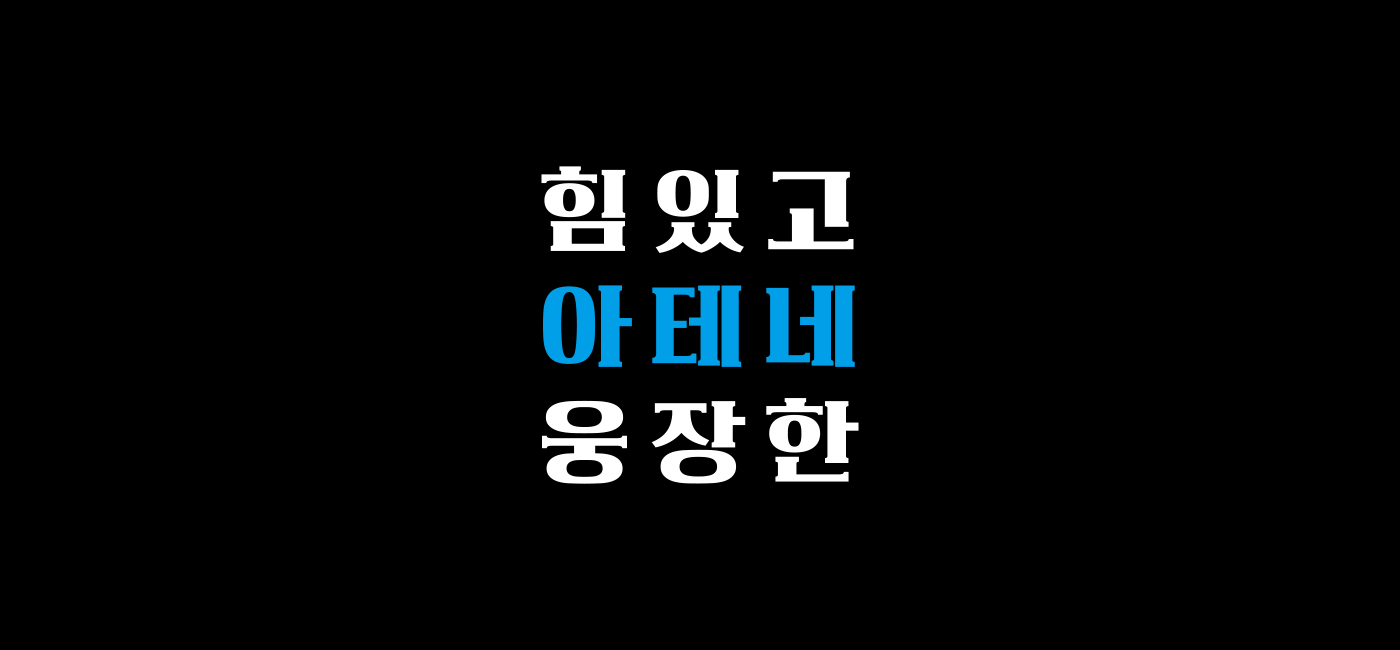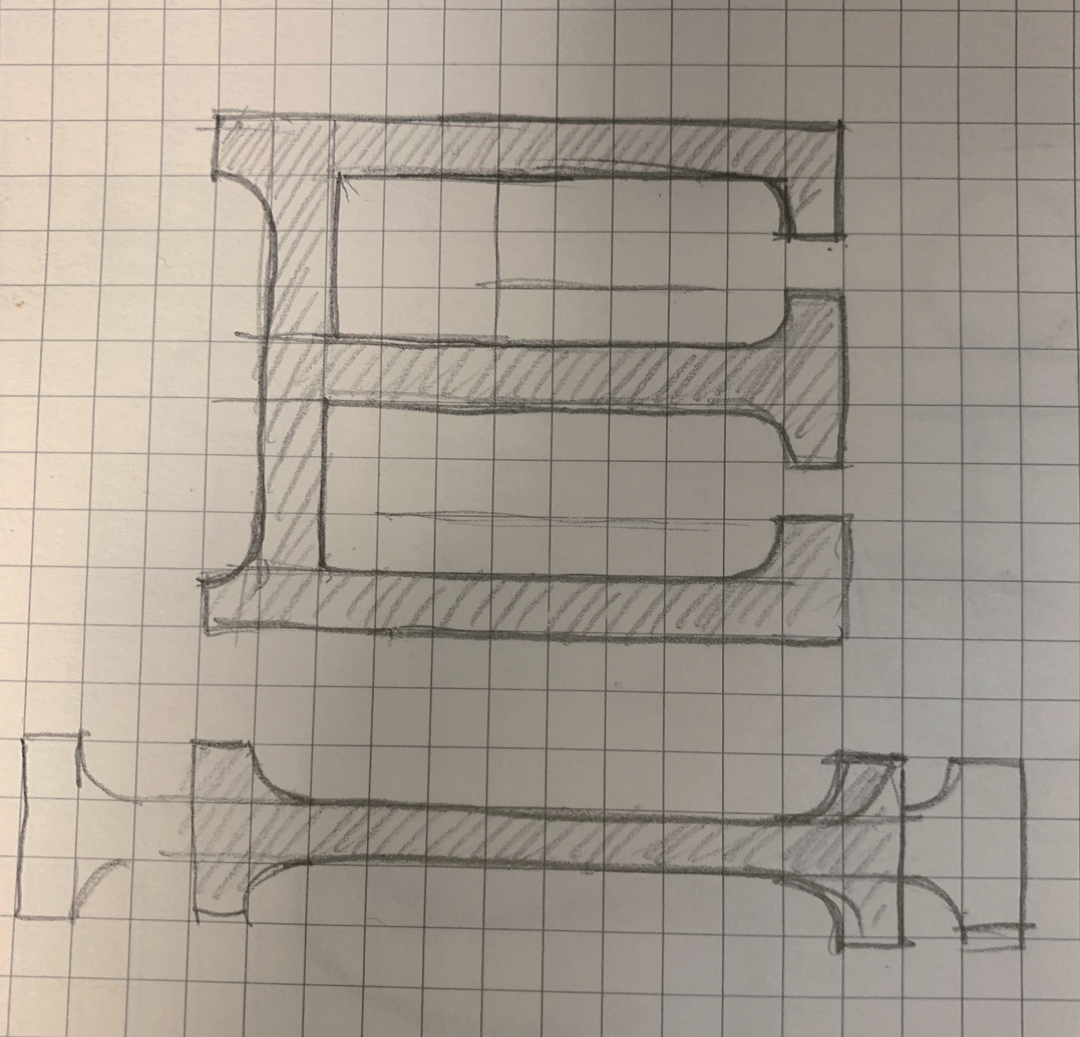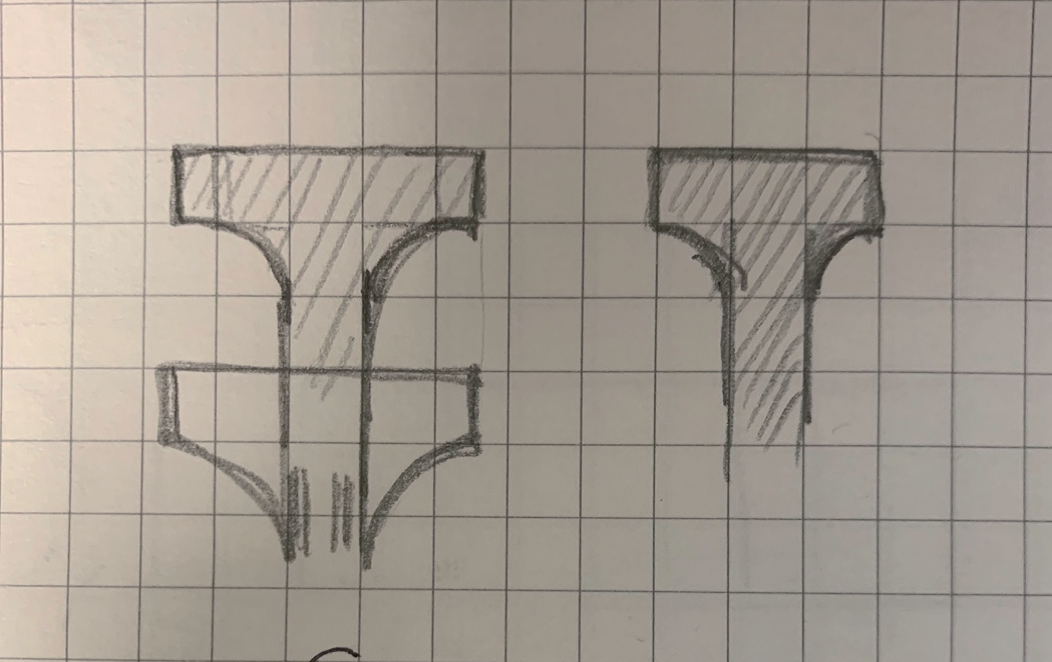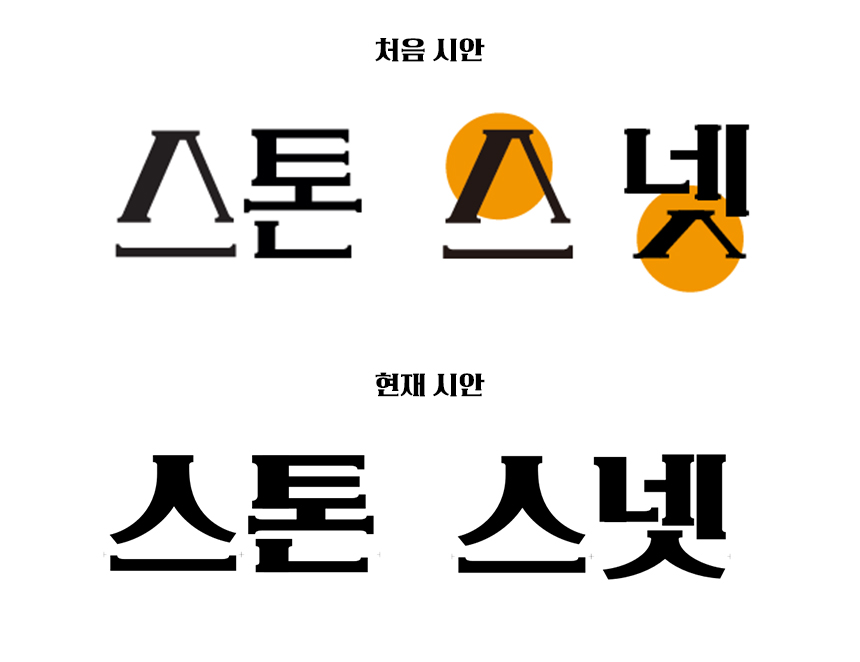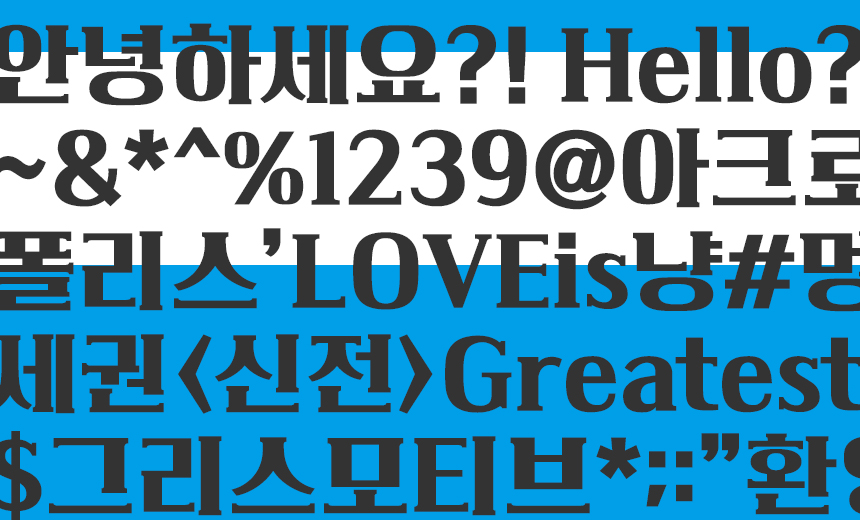
안녕하세요. 오늘은 12월의 신규 폰트 「Rix아테네」를 소개합니다. 폰트명에서 느껴지듯 그리스의 수도이자 최대 도시인 아테네에 있는 신전의 웅장함을 담은 서체입니다. 화려함과 클래식한 美가 공존하는 Rix아테네. 폰트를 디자인한 이지윤 디자이너와의 인터뷰를 통해 더 자세히 알아볼게요-!
12월에 선보이는 신서체 Rix아테네는 어떤 폰트인가요?
OTT 서비스 중 넷플릭스를 자주 사용하는데, 주로 시청하는 미드나 영미 영화 제목은 기존 서체를 사용하거나 장식적인 부분을 추가/변형해서 사용하는 것 같더라고요. OTT 서비스에서 쉽게 사용할 수 있는, 눈에 잘 띄는 제목용 서체가 있으면 좋겠다는 생각에 Rix아테네를 기획하게 되었습니다. 특히 눈길을 끄는 제목의 특징을 보면 두드러지는 획 대비와 장식적인 세리프, 그리고 꽉 찬 골격을 가지고 있음을 알게 되었습니다. 이러한 특징을 반영한 서체를 만들어보고 싶었습니다.
아테네 폰트에서 주목할만한 포인트가 있다면?
Rix아테네의 특징이라고 하면 세리프 형태, 그리고 ‘ㅅ’과 ‘ㅈ’의 자소 형태입니다. 처음에는 세리프의 크기와 형태에 대한 고민이 제일 컸어요. 눈에 거슬리지 않을 정도의 크기면서도 형태가 잘 보였으면 좋겠다는 생각에 크게, 또 작게 보면서 적절한 세리프의 두께와 크기를 찾아갔습니다.
또 세리프가 단순한 장식으로서 존재하기보다는 전체적인 컨셉과 느낌을 주도했으면 좋겠다는 생각에 그리스 신전/기둥을 모티브로 삼고 세리프의 형태를 다듬어 갔습니다.(그래서 서체 이름도 Rix아테네이고요!) 처음 시안과 비교해 보면, 획 굵기도 얇고 세리프의 크기도 작아서 뾰족해 보여요. 현재 시안에서는 이를 보완하기 위해 두께와 크기를 살짝 키웠습니다. 그다음으로 신경 쓴 건 갈래와 빗침과 갈래가 있는 자소들의 형태였습니다. 원래는 그리스 신전 느낌을 살리기 위해 전체적으로 직선적인 형태로 제작했었습니다. 그런데 초기 시안과 같은 형태의 'ㅅ'을 받침으로 사용할 경우 어딘가 부자연스럽고 딱딱한 느낌이 들어서 현재 시안과 같이 형태를 바꾸게 되었습니다. 꽉 찬 골격과 직선적인 획들 사이에 곡선이 들어가니 오히려 자연스럽고 부드러워 보이더라고요.
서체가 어떻게 쓰였으면 좋을지?
아무래도 OTT 서비스를 사용하며 처음 아이디어가 나왔으니 넷플릭스, 왓챠, 쿠팡 플레이, 등 국내외 OTT 채널들에서 많이 보이면 좋을 것 같아요.
그리스 신전을 닮은 세리프
그리스 문명의 상징적인 건축물인 파르테논 신전을 보면 고고함과 웅장함을 느낄 수 있는데요, Rix아테네는 이러한 조각물의 아름다운 형태와 견고한 구조 등을 모티브로 제작되었습니다.
고대 건축물의 단단한 기둥 양식을 닮은 두꺼운 획과 장식적인 세리프, 폭이 넓고 꽉 찬 골격의 형태가 전체적으로 조화롭게 어우러진 특징이 있습니다.
강인함과 부드러움의 공존
그리스 신전의 느낌을 담은 세리프와 자연스럽게 어우러지는 디자인에 주목해 보면, 원형 형태의 직선 구간과 획 대비가 고전적이고 클래식한 이미지에 힘을 실어줍니다. 그리고 세리프의 곡선과 어울리도록 자소 'ㅅ', 'ㅈ' 등에서 보이는 유려한 곡선으로 부드러운 인상을 더해주었습니다.
단단하고 강인한 인상과 부드럽고 유려한 인상이 함께 느껴지며 조화로운 디자인을 갖춘 Rix아테네. 특색 있는 제목용 서체로서 높은 주목도가 필요하거나 컨셉이 있는 콘텐츠에 활용하기 좋을 것 같습니다.
이렇게 활용해 보세요🏛️
눈길을 끌어야 하는 웹페이지 배너나 영화 포스터 이미지에 적용해 본 모습입니다. 특징적이고 강렬한 분위기로 여행이나 영화, 게임 등 컨셉추얼 한 콘텐츠의 메인 타이틀 서체로 쓰기 좋습니다.
여러 글자를 써보니 자소 'ㅍ'에서 그리스 신전의 기둥 느낌이 특히 잘 드러나는 것 같아요! 주목도가 높고 장식적인 세리프는 보통 획 대비가 아주 강한 디자인이 많은데, Rix아테네는 획 대비가 자연스럽고 적절해 다양한 콘텐츠에서 활용도가 높을 것으로 보입니다.